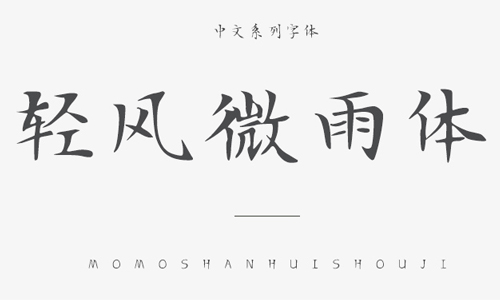
輕風(fēng)微雨體字體是一款具有楷書特色的手寫字體,筆觸細(xì)膩而軟硬兼具,具有古風(fēng)字體韻味的特色魅力,給藝術(shù)設(shè)計(jì)增添獨(dú)特魅力,且字庫完整,可以滿足設(shè)計(jì)師們的工作需要,字跡清新而端莊,有著極佳的閱讀好感。能夠應(yīng)用于文本裝潢、信息展示、網(wǎng)頁設(shè)計(jì)、篆刻制模、數(shù)據(jù)制作、裝潢設(shè)計(jì)、計(jì)算藝術(shù)設(shè)計(jì)、視覺設(shè)計(jì)、字帖等一切合法應(yīng)用場(chǎng)景,歡迎有需要的朋友們前來下載使用。